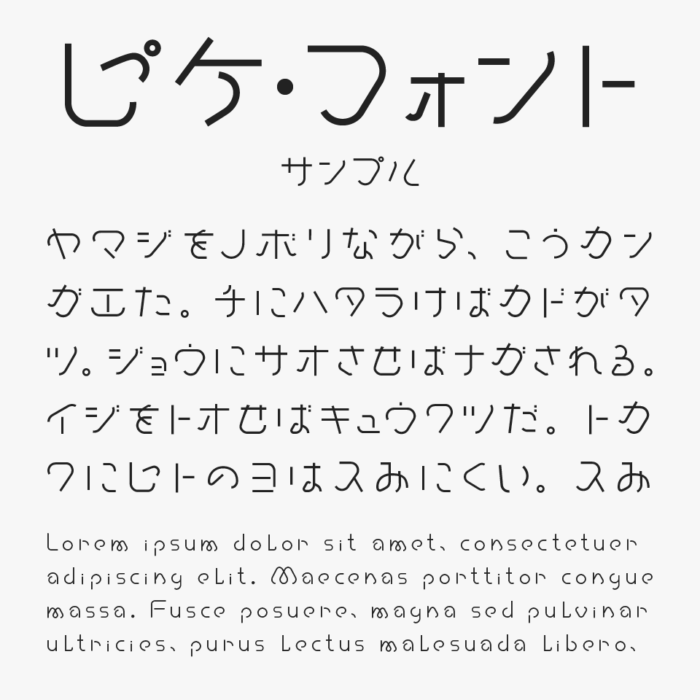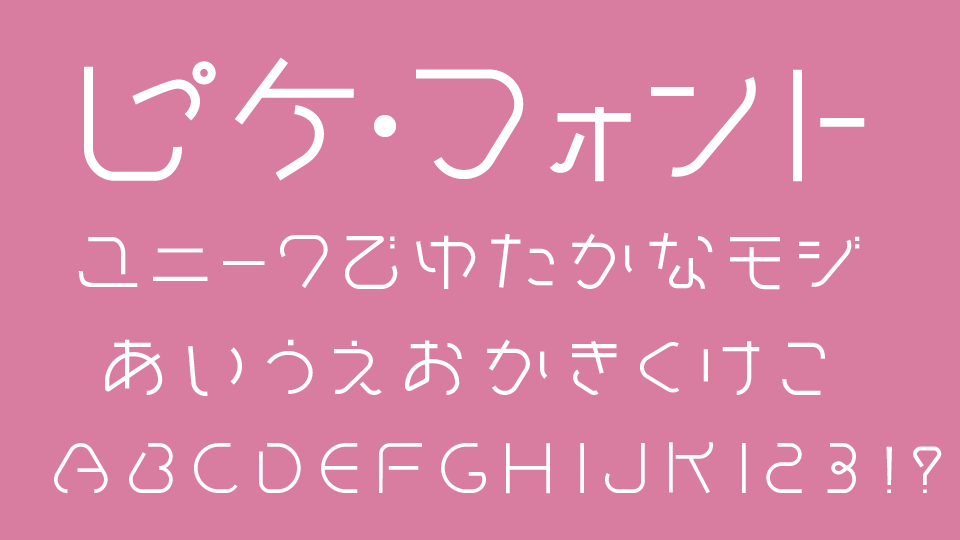
ピケ・フォントは、極細のストロークと大きく開いた曲線が特徴的な、スッと抜けるような軽さを持つデザインフォントです。
コンセプトが「パジャマパーティやくつろぎ感ある部屋着をイメージしてつくった」ということで、線の端がすべて丸く処理されており、尖った部分がどこにもないため、ゆったりとした全体を通して穏やかで空気感のあるとても可愛らしいフォントです。